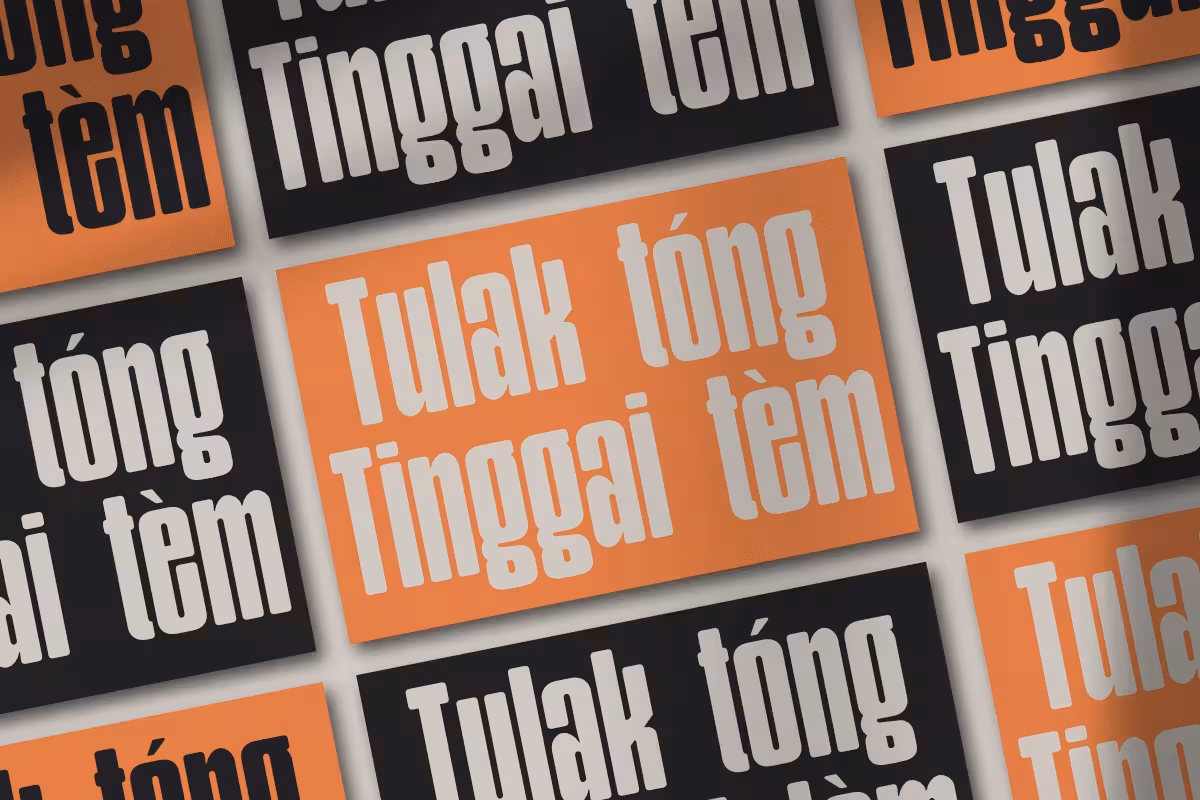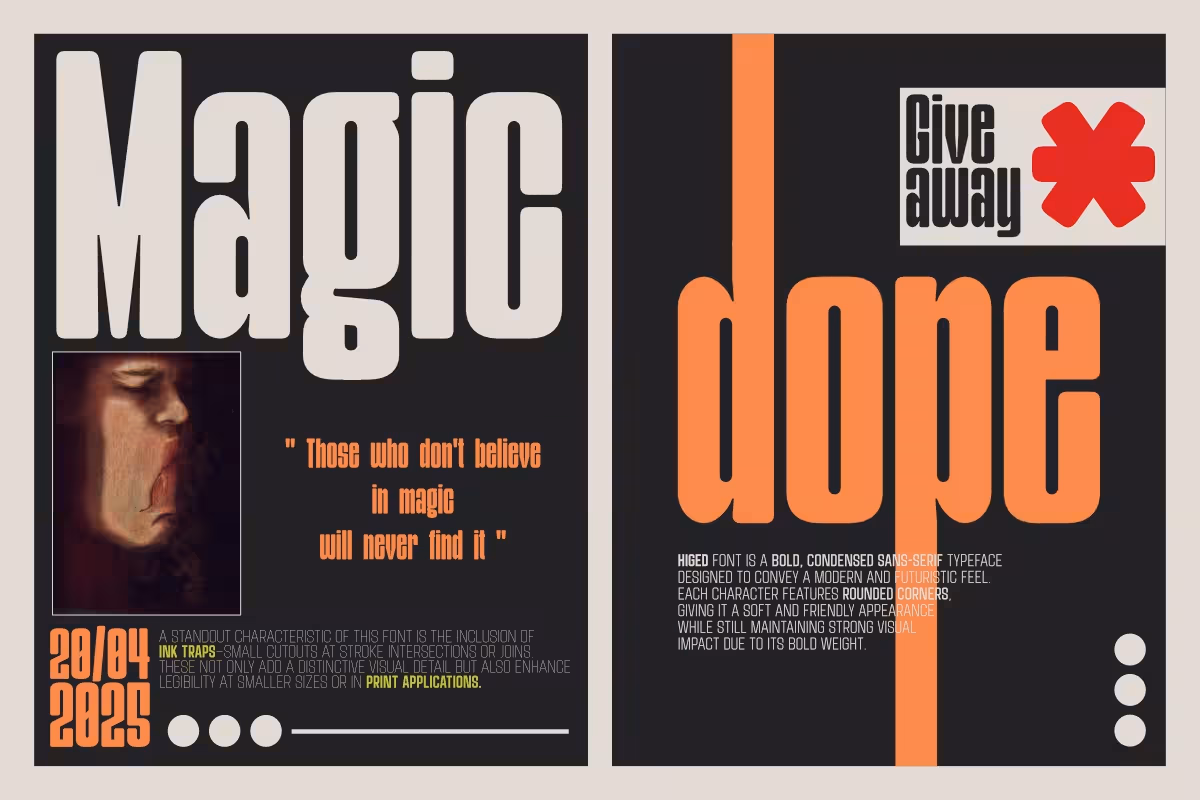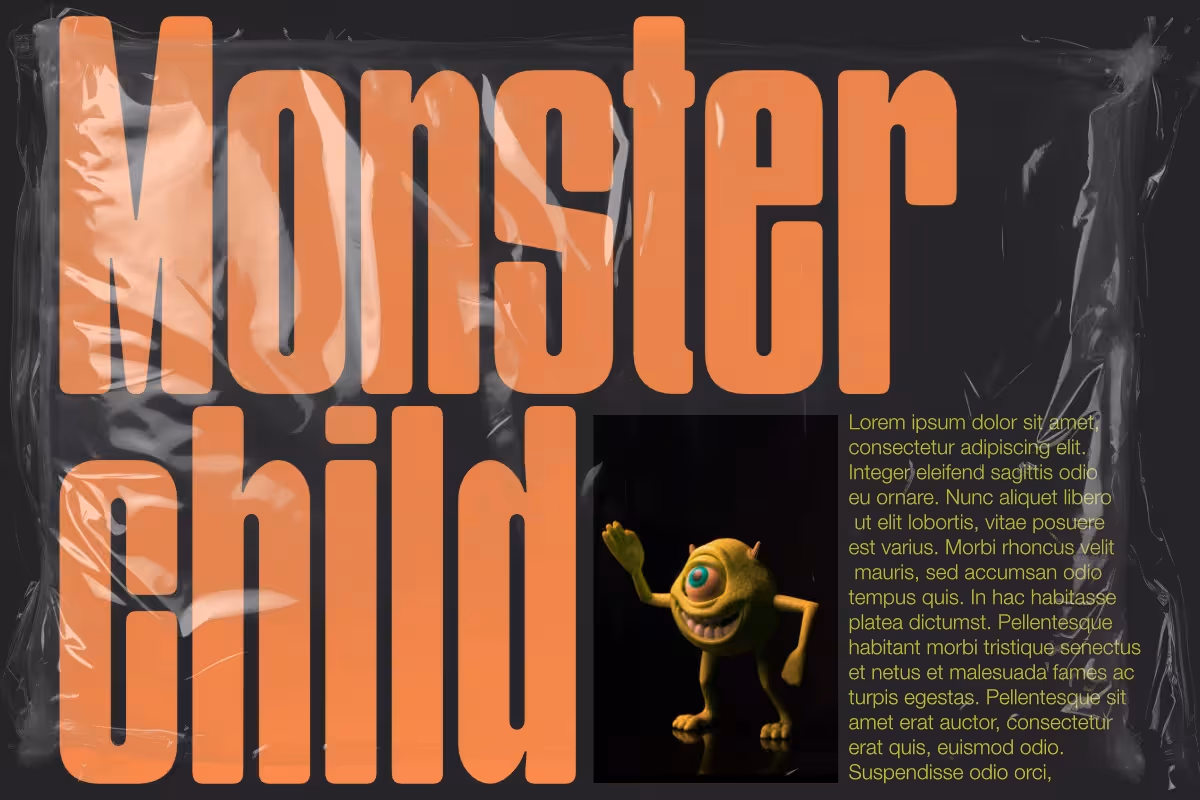
Giới thiệu về Font TF Higet Việt hóa
TF Higet Việt hóa là một font chữ nổi bật với thiết kế dáng cao, tròn trịa và cực kỳ dễ thương, mang đến vẻ ngoài tươi sáng, hồn nhiên và đầy cuốn hút. Font này gợi cảm giác về sự mềm mại, thân thiện và năng động, lý tưởng để thu hút sự chú ý và tạo ra một không khí vui vẻ.
Với đặc điểm hình dáng độc đáo – cao, tròn và dễ thương – Higet là lựa chọn lý tưởng cho các thiết kế muốn truyền tải sự vui tươi, đáng yêu và sự gần gũi, đặc biệt là trong các lĩnh vực:
- Thiết kế poster: Hoàn hảo để tạo các tiêu đề chính, thông tin sự kiện hoặc nội dung quảng cáo trên poster. Dáng cao và rõ ràng của font giúp tiêu đề nổi bật, dễ đọc và truyền tải thông điệp một cách hiệu quả, đặc biệt cho các sự kiện vui nhộn hoặc quảng bá sản phẩm.
- Tiêu đề: Lý tưởng cho các tiêu đề trong các ấn phẩm, bài viết trên mạng xã hội hoặc các slide thuyết trình. Nét tròn dễ thương làm cho tiêu đề trở nên thân thiện và dễ chịu hơn, thu hút người xem.
- Thiết kế ẩm thực: Tuyệt vời cho menu quán kem, trà sữa, cửa hàng bánh kẹo, hoặc bao bì sản phẩm đồ ăn vặt. Font này giúp gợi cảm giác ngon miệng, ngọt ngào và thân thiện, làm cho các món ăn thêm phần hấp dẫn.
- Thiết kế cho trẻ em: Phù hợp cho sách truyện thiếu nhi, đồ dùng học tập, bảng hiệu trường mầm non, đồ chơi, hoặc các ấn phẩm giáo dục. Font này giúp tạo không khí ngộ nghĩnh và thân thiện với trẻ nhỏ.
Với TF Higet Việt hóa, bạn có thể dễ dàng thổi hồn vui tươi, đáng yêu và sự tươi mới vào các thiết kế, tạo ra những sản phẩm không chỉ đẹp mắt mà còn đầy cảm xúc và sức hút đặc biệt.
Font Việt hóa TF Higet – Phong chữ to trò ẩm thực